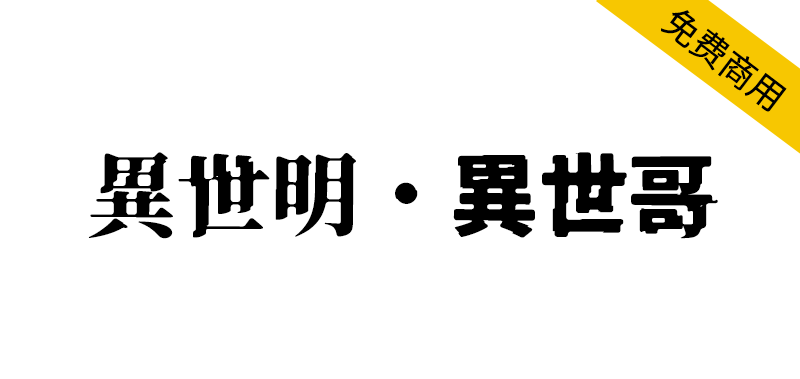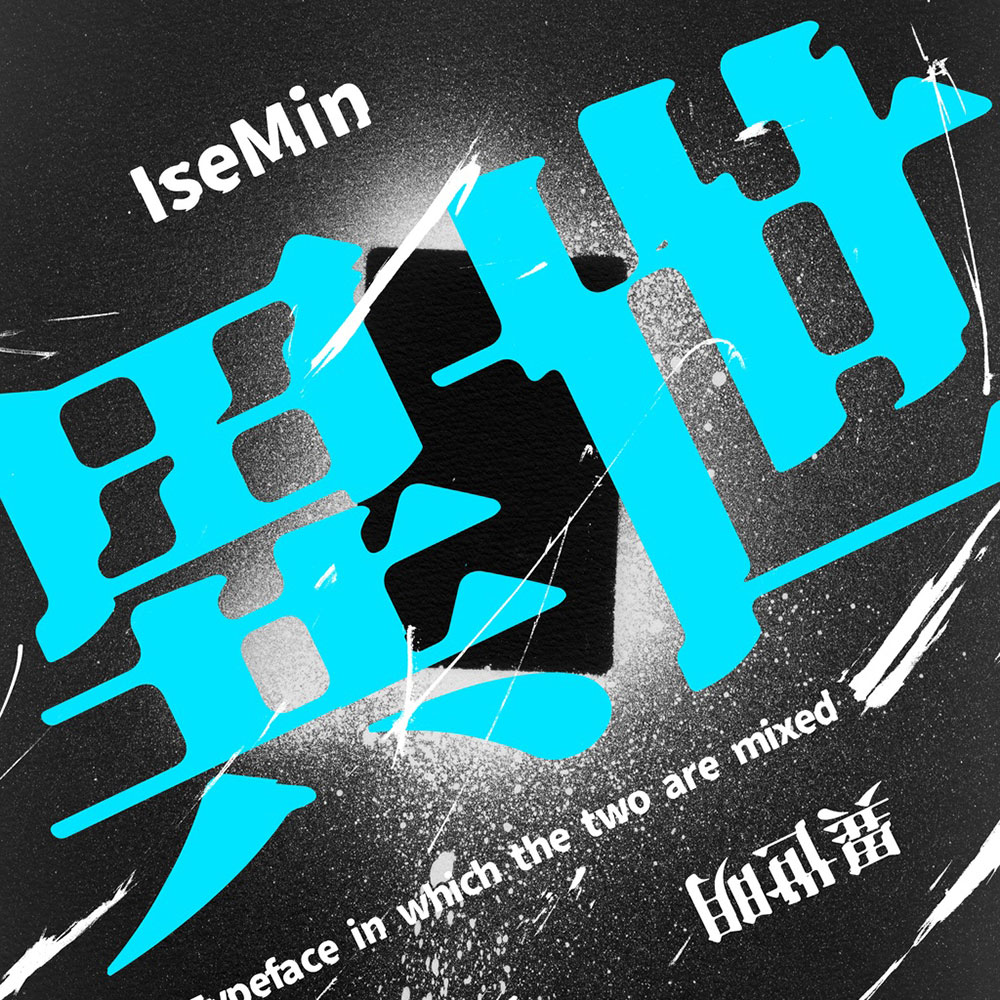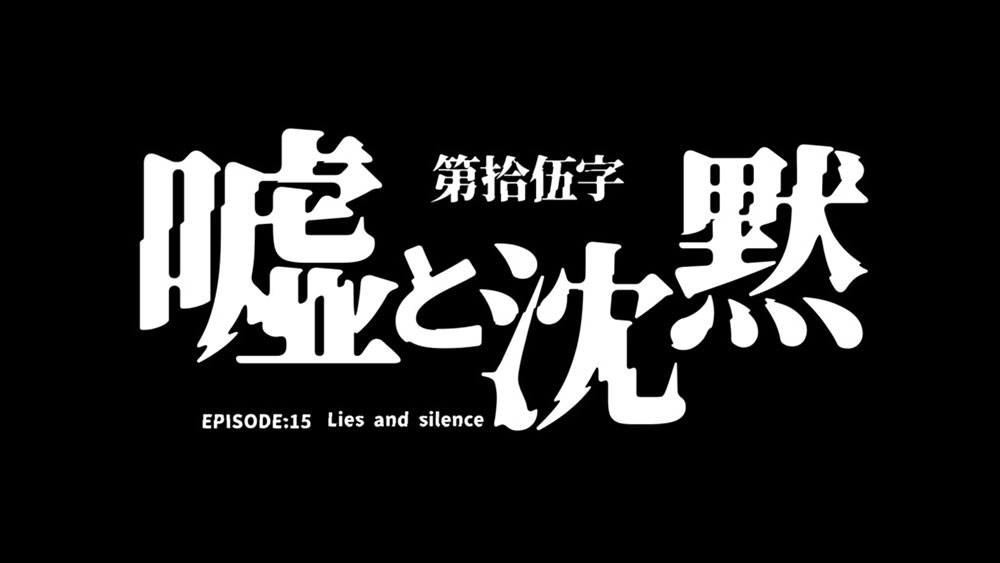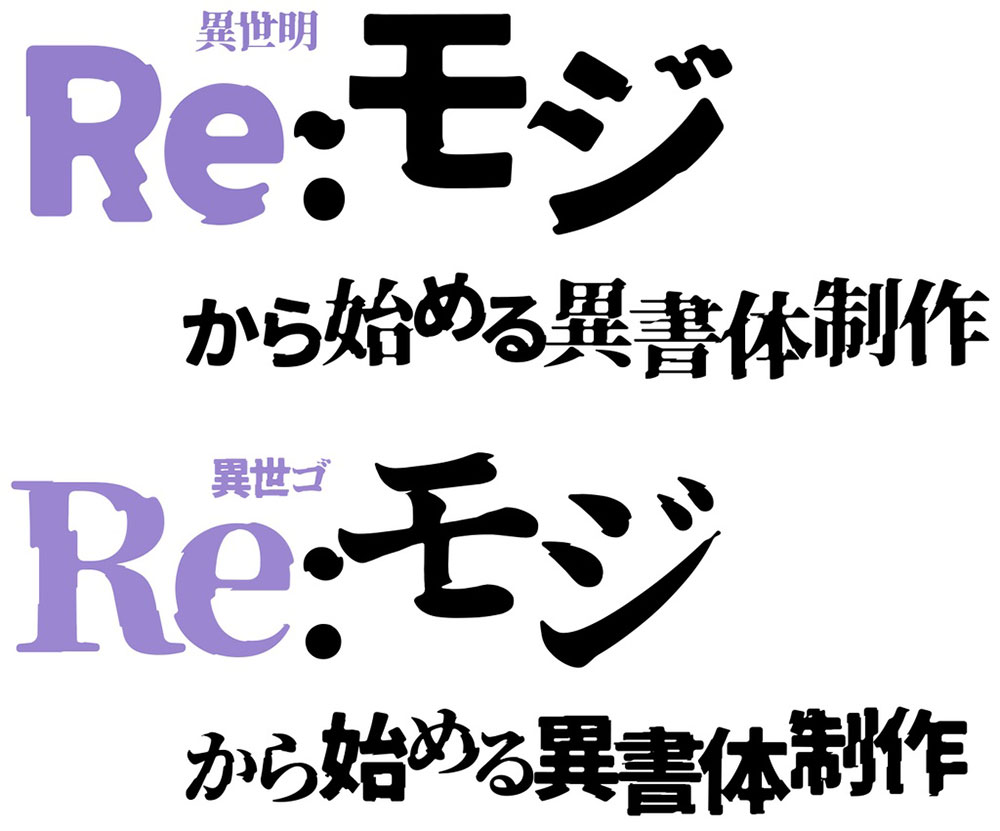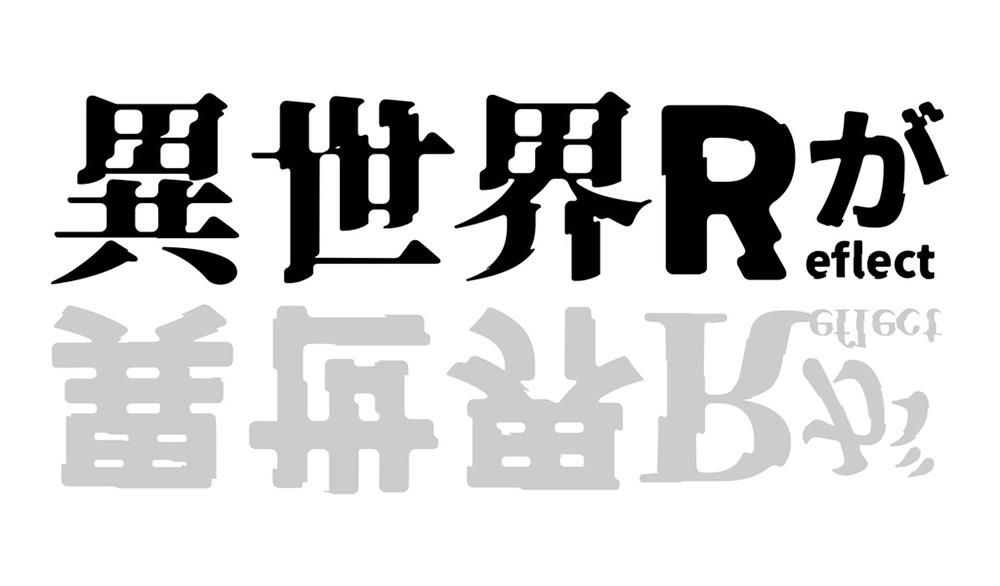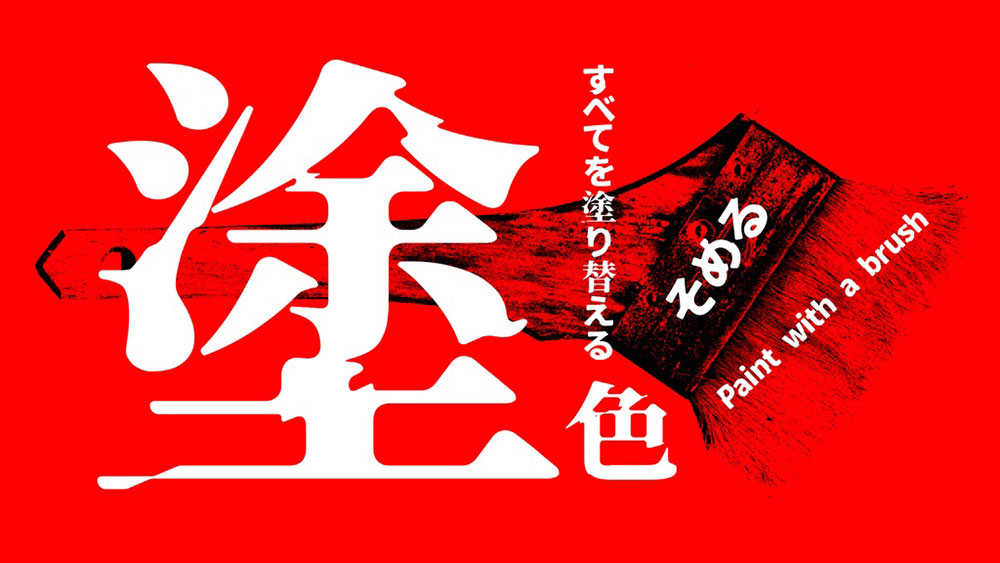
异世明·异世哥(異世明・異世ゴ)基于日本版的「思源宋体」「思源黑体」创作而成,字体通过扭曲变形效果,生动再现了"穿越异世界时空间扭曲"的奇幻感,给人一种崩溃的感觉,属于极具特色的标题、LOGO专用字体。根据IL Open Font License 1.1授权协议发布,可自由用使用、自由修改、自由发布。
異世明・異世ゴの2つのフォントのセットです。「異世明」は漢字が明朝体で、その他の文字がゴシック体のフォントです。逆に「異世ゴ」は漢字がゴシック体で、その他の文字が明朝体のフォントです。
異世界に転移(ワープ)するときに「ぐにゃ」っと世界が歪むような崩れた感じのデザインになっています。かなり特殊な見出し・ロゴ向けのフォントに属すると思います。